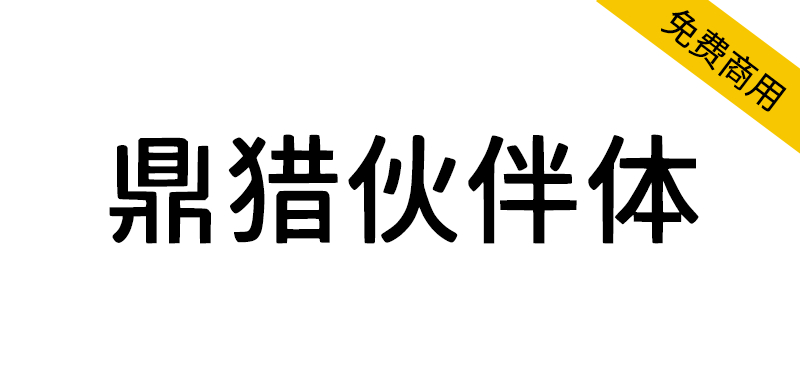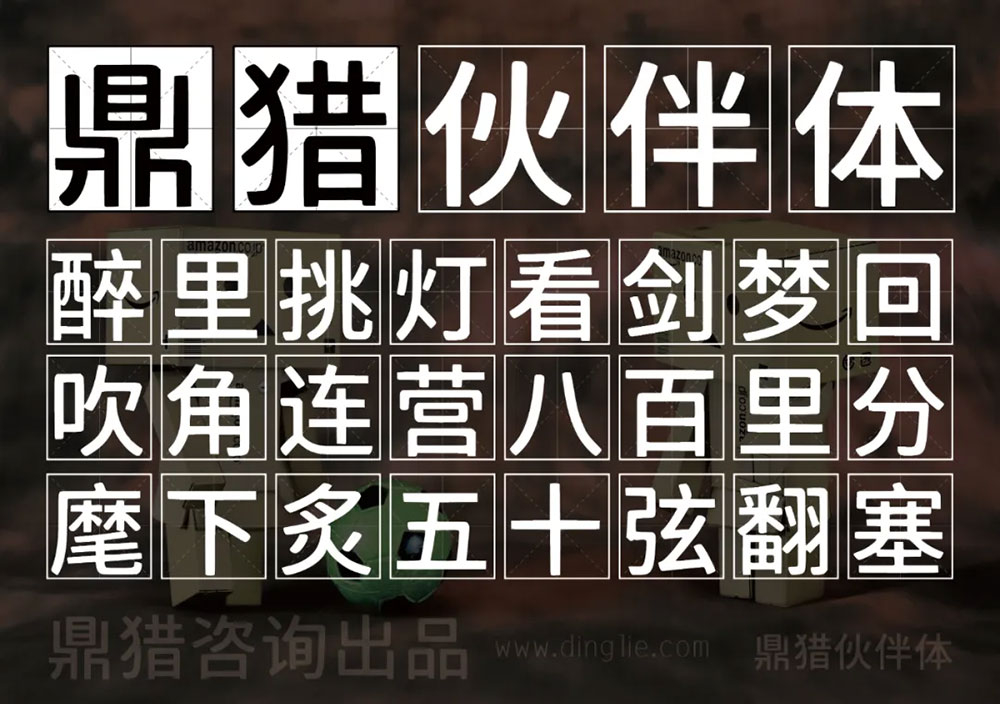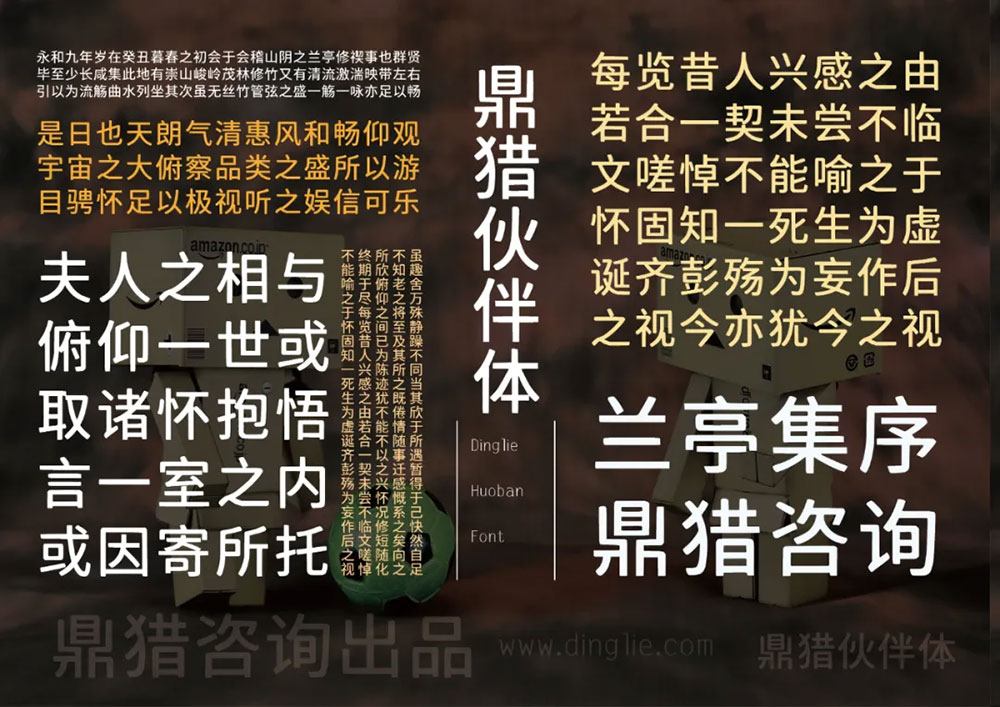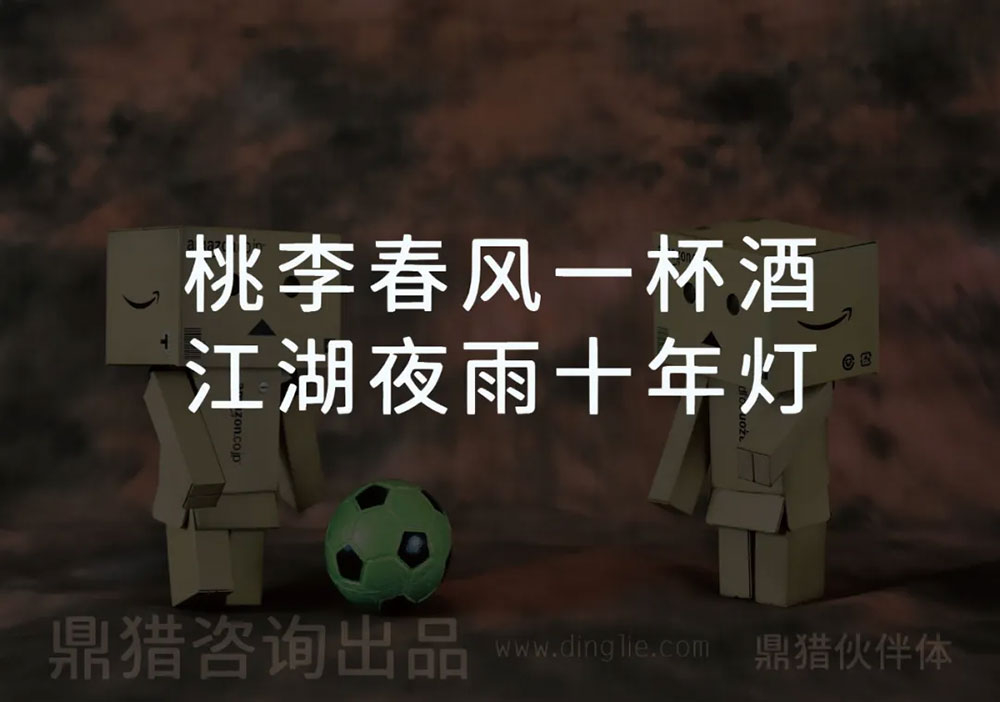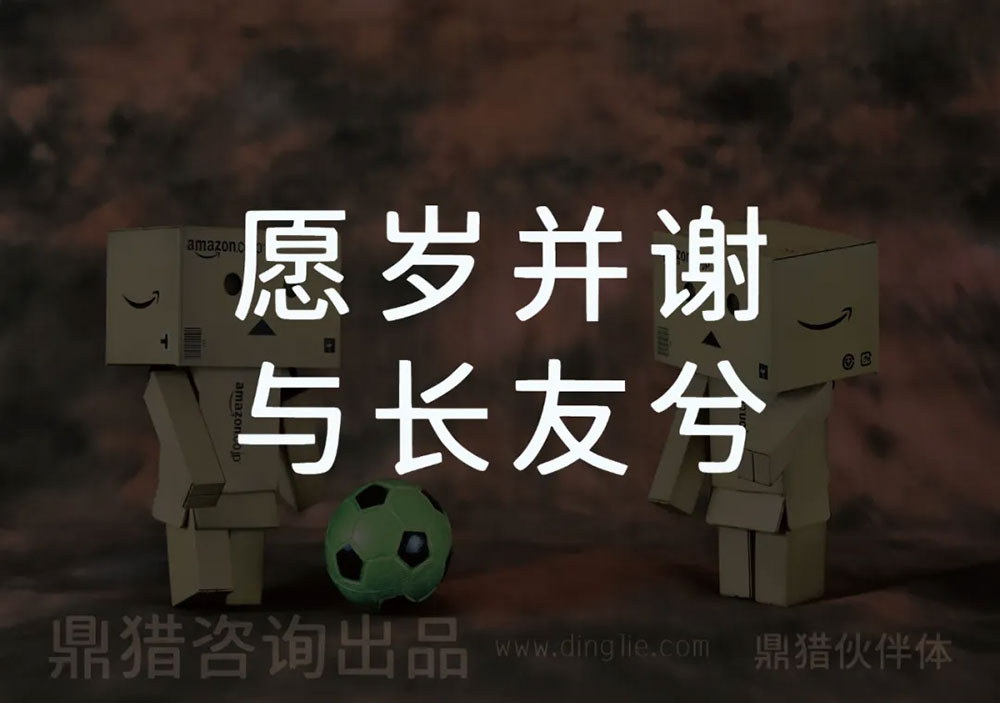
鼎猎伙伴体,为一款原创多应用场景黑体字,适合美食餐饮、文化艺术展览、企业文化,以及封面杂志海报、餐饮茶饮、美妆护肤等各个行业。马上踏入2025年了,这套字体姗姗来迟,终于到了发布的时候。
考虑到字体应尽可能满足各类型的姓和名,鼎猎伙伴体以简体中文汉字编码国家标准(GB2312编码)为标准,共计设计了多达7415个字符,其中汉字6769个。可以满足绝大部分印刷设计等要求。